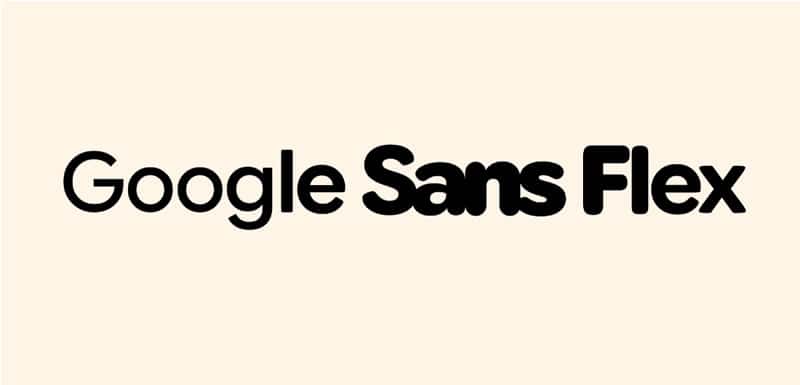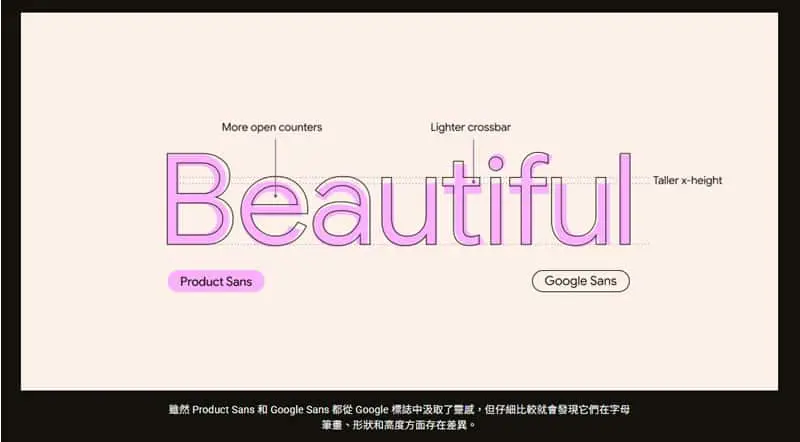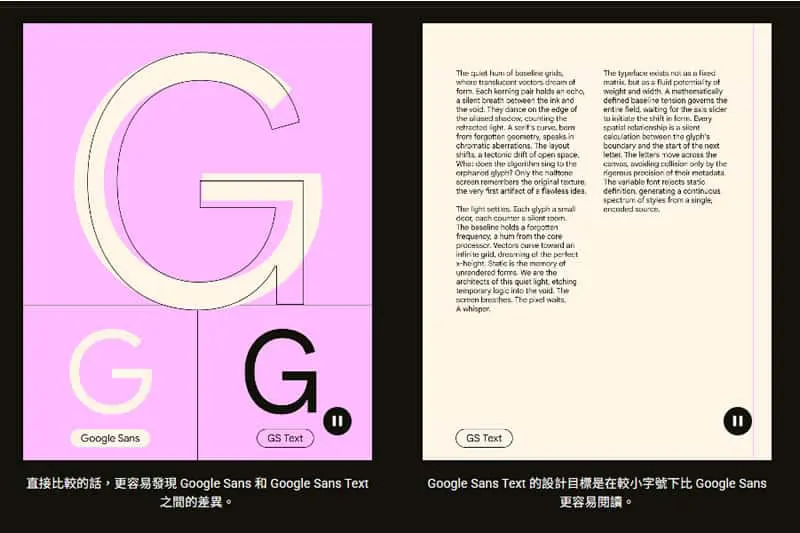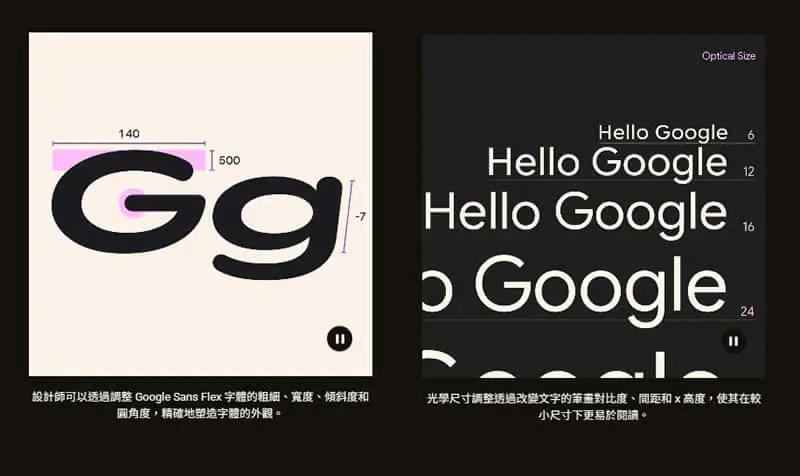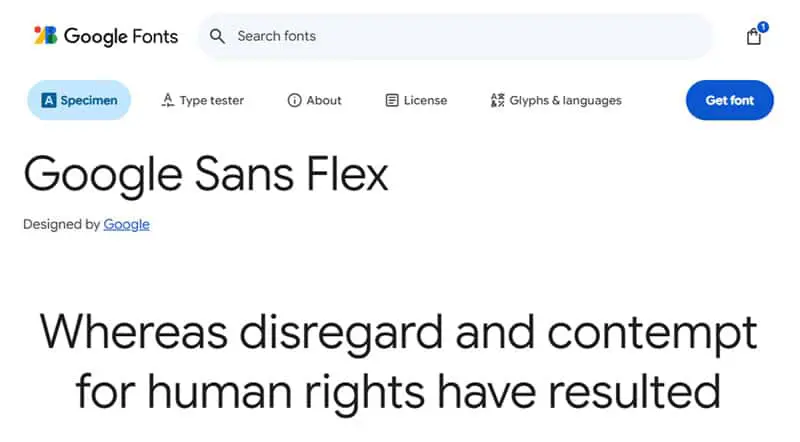
專案若有需要不同粗細的字體,大部分應該都會碰到要下載一大堆字型檔案,每個檔案都只是粗細不同而已?或是想調整字體寬度,卻發現根本沒有合適的選項?
好消息來了!Google 在 2025 年正式將旗下品牌字體「Google Sans Flex」開源,而且完全免費、可商用。更棒的是,這是一款「可變字體」(Variable Font),意思是你只需要下載一個檔案,就能自由調整粗細、寬度等六種不同的參數。
Google Sans 是 Google 自 2015 年重新設計品牌識別後使用的官方字體,你在 Gmail、Google 搜尋、YouTube 等各種 Google 產品上看到的文字,幾乎都是用這款字體。
而 Google Sans Flex 是這個字體家族的最新成員,也是技術上最先進的一款。它採用「可變字體」技術,讓設計師和開發者能用單一字體檔案,就創造出數千種不同的視覺效果。
這款字體有多熱門?根據 Google 官方數據,Google Sans 每個月在全球有超過 120 億次的字體請求。現在這款字體開源了,任何人都能免費使用,甚至用在商業專案上也完全合法。
Google Sans 的演進故事:七個設計問題塑造一款字體
Google Sans 不是一夕之間誕生的,而是經過近十年的演進,針對各種實際使用問題逐步優化。讓我們快速瀏覽一下它的發展歷程:
1. 產品標識與新 Logo 不搭(2015)
2015 年 Google 重新設計 Logo 後,發現數百個產品的標識(像是「Google Maps」、「Google Drive」這些名稱)都需要配合更新。於是他們創造了 Product Sans,一款基於新 Logo 幾何形狀設計的字體。
2. Product Sans 不適合行銷和介面使用
設計師們很快發現 Product Sans 雖然用在大標題很漂亮,但用在廣告或手機介面的小字上就不夠清晰。於是 Google Sans 誕生了,專門優化了字母形狀、高度和筆劃對比,讓它在各種尺寸下都好看又好讀。
3. 小字還是不夠清楚
即使有了 Google Sans,在小尺寸下的可讀性還是不夠理想。2020 年,Google 推出了 Google Sans Text(GST),字母更高、更窄、間距更寬,專門用於小字顯示。這個版本也考量到要跟 Android 預設字體 Roboto 的比例相符,方便切換。
4. 只支援歐洲語言
一開始 Google Sans 只有拉丁字母,但 Google 的產品是全球化的啊!於是他們展開了一項龐大工程,與全球 20 多個專業字型工作室合作,為阿拉伯文、中文、泰文、日文、韓文等超過 20 種書寫系統設計對應字體。這讓 Google Sans 成為世界上最大的字體家族之一。
5. 無法表達情感和個性
隨著介面越來越動態、個人化,設計師需要的不只是「清楚好讀」的字體,還要能傳達「感覺」和「情緒」。傳統字體只有幾種固定樣式(粗體、斜體等),彈性不夠。
這就是 Google Sans Flex 誕生的原因。
6. 只有 Google 能用
雖然 Google Sans 很棒,但一直以來都是 Google 的專屬品牌字體,第三方開發者和設計師無法使用。這造成了一個問題:你在 Gmail 看到的是 Google Sans,切換到 WhatsApp 就變成 Roboto 或其他字體,視覺體驗不連貫。
2025 年,Google 決定將 Google Sans 和 Google Sans Flex 開源,任何人都能免費使用。這不只是開放資源,更是希望創造一個更統一、更優質的數位環境。
Google Sans Flex 的六大可變軸:讓一款字體抵千款
好,現在進入重點:什麼是「可變軸」?為什麼它值得你關注?
傳統字體如果要不同的粗細,你得下載「細體」、「標準體」、「粗體」、「特粗體」等多個檔案。但可變字體只需要一個檔案,就能在這些樣式之間「無段調整」。
Google Sans Flex 提供了六個可變軸:
1. Weight(字重)
從極細的 Thin 100 到超粗的 Black 900,你可以精確調整到任何數值,比如 350 或 625。
2. Width(寬度)
讓字體變窄或變寬,適應不同的版面需求。
3. Optical Size(光學大小)
這個軸會智慧調整字母形狀,讓字體在手錶螢幕或大型看板上都保持最佳可讀性。
4. Slant(傾斜)
類似斜體,但可以精確控制傾斜角度。
5. Grade(等級)
在不改變字體寬度的情況下,調整筆劃的粗細,用來微調視覺重量。
6. Roundness(圓潤度)
這是設計師最愛的功能!可以調整字體的圓潤或尖銳程度,讓文字感覺「溫暖親切」或「銳利專業」。
透過這六個軸的組合,你可以創造出數千種不同的視覺風格,而且都來自同一個字體檔案。這不僅節省檔案空間,也讓設計流程更有彈性。
一個小遺憾:目前沒有中文
如果你看到這裡,可能會想問:「那中文呢?」
很遺憾,Google Sans Flex 目前只支援拉丁字母,也就是英文、法文、德文等歐洲語言。雖然 Google Sans 家族有支援中文、日文、韓文等多種語言,但 Flex 這個可變字體版本暫時還沒有。
為什麼 Google 要開源字體?
你可能會好奇:「Google 為什麼要把自己的品牌字體開源?」
根據 Google 設計團隊的說法,主要有幾個原因:
1. 創造更一致的使用體驗:讓第三方 App 也能用 Google Sans,減少視覺上的跳躍感
2. 推廣可變字體技術:鼓勵更多開發者和設計師使用這項先進技術
3. 回饋設計社群:Google 從開源社群獲益良多,也希望回饋貢獻
這個決定不只對設計師有利,對一般使用者來說,也意味著未來我們使用的 App 和網站會有更統一、更優質的視覺體驗。
結語:字體的未來,就在你手中
Google Sans Flex 的開源,不只是 Google 的一次慷慨分享,更是字體技術演進的一個里程碑。可變字體代表了未來的趨勢:更少的檔案、更多的彈性、更好的使用體驗。
現在,這個每月被請求 120 億次的字體,已經向所有人開放。無論你是專業設計師、網頁開發者,還是只是想為個人專案找個好看的字體,Google Sans Flex 都是一個值得收藏的選擇。